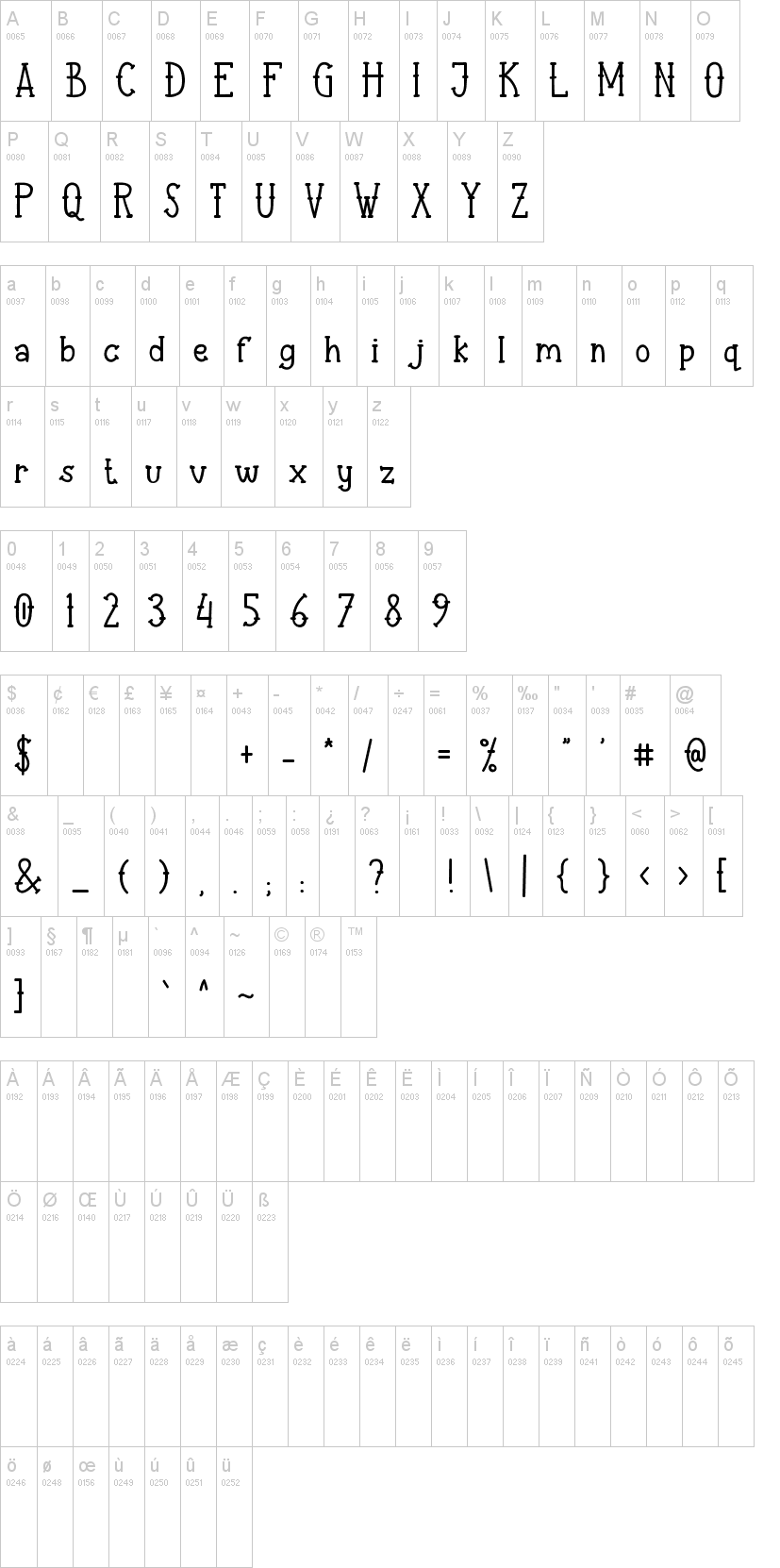
Aye Matey 是一款由FontMesa创作的手写字体,它拥有海盗般的风格,具有轻松、有趣的气息,可以用于海盗、海洋、欢乐等主题的设计中。它具有清晰的轮廓和视觉效果,可以为您的设计增添一抹活力,并使其看起来更有趣。Aye Matey 字体的大小可以从 8 到 72 磅不等,支持多种语言,包括英语、法语、德语、西班牙语、意大利语等,可以用于各种设计项目,如海报、品牌标识、T恤、卡片、海报、礼品盒等。内容介绍
Aye Matey是一款非常不错的手写艺术字体,具有很好的视觉感,适合于文化类的宣传设计、商业类品牌的广告和产品包装设计以及个性化文字排版等较多场景。